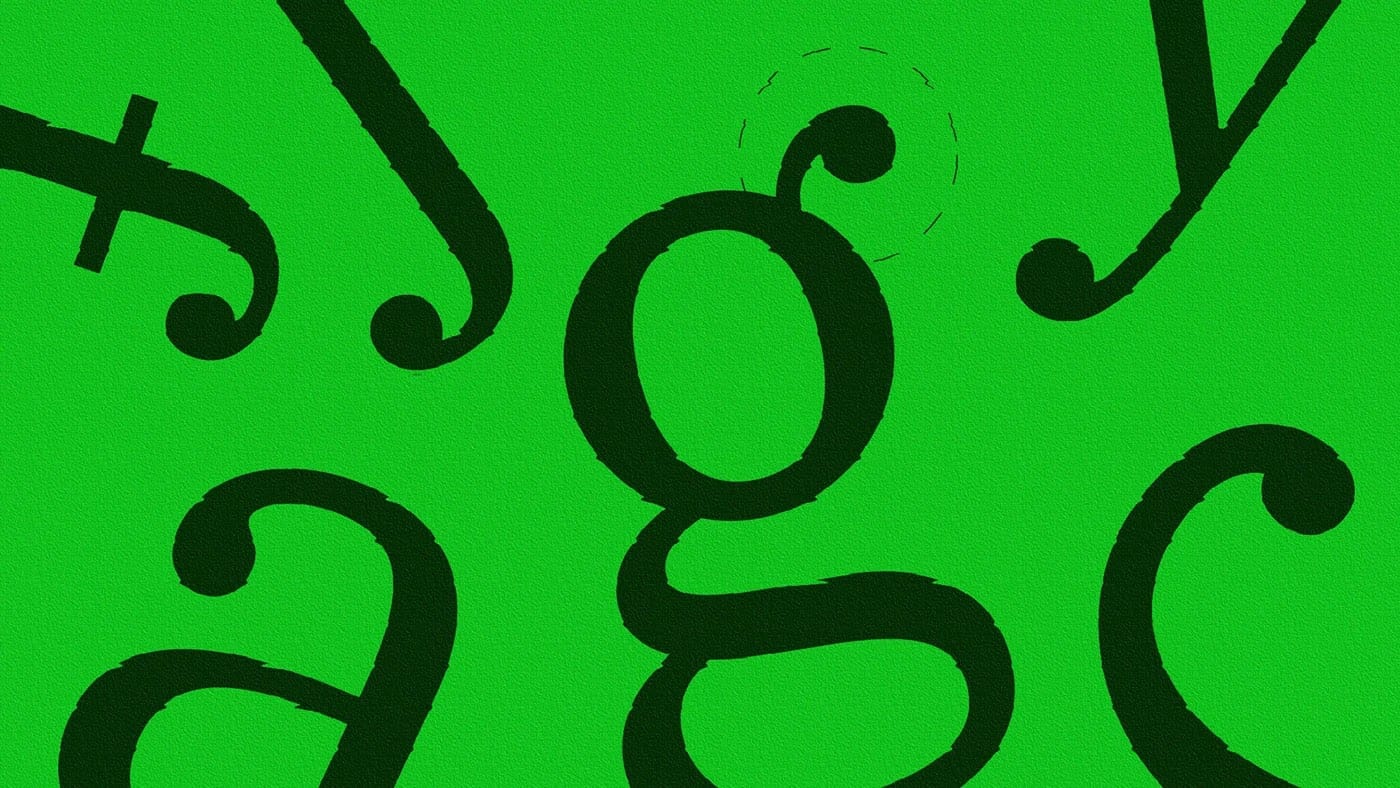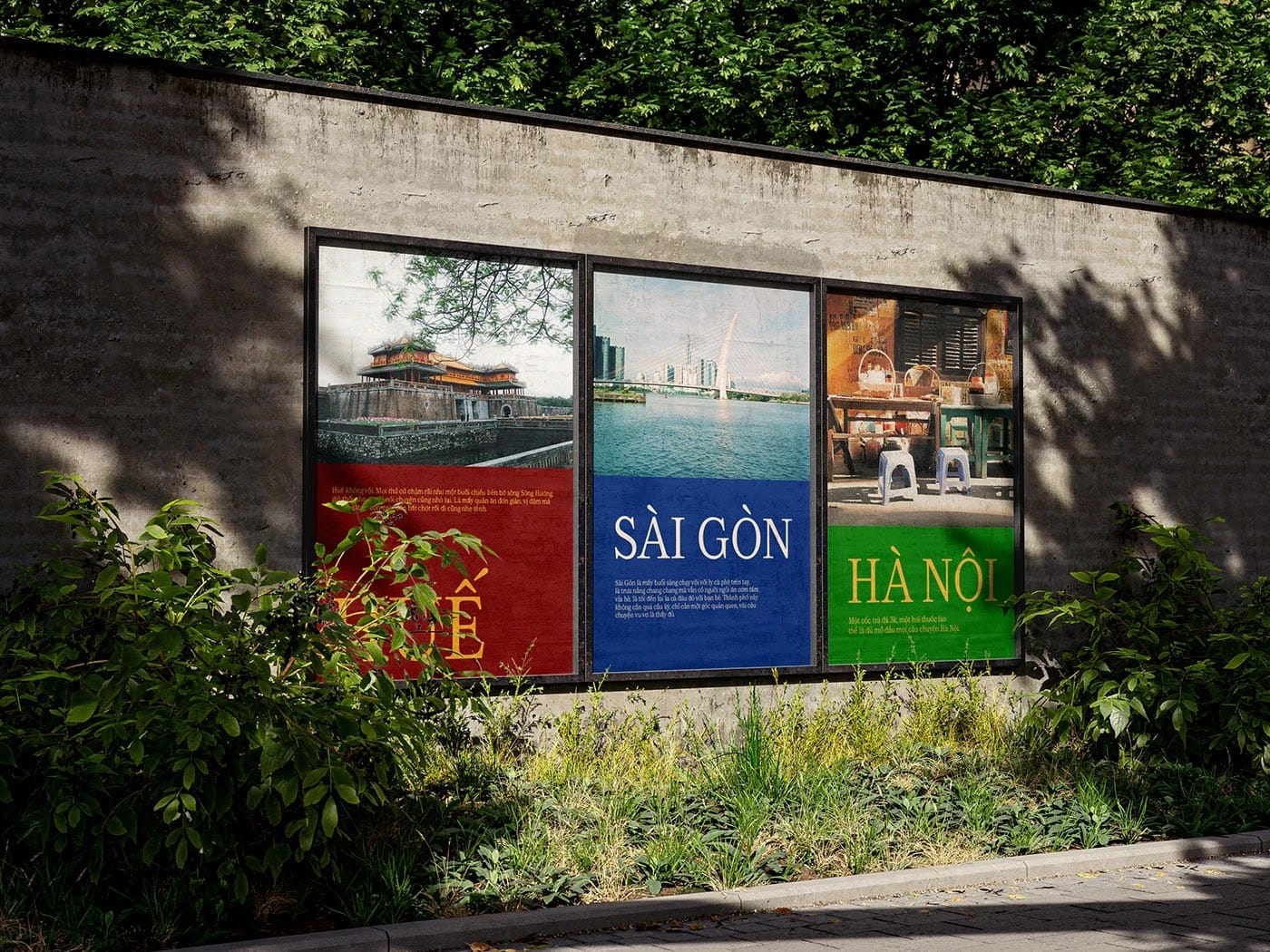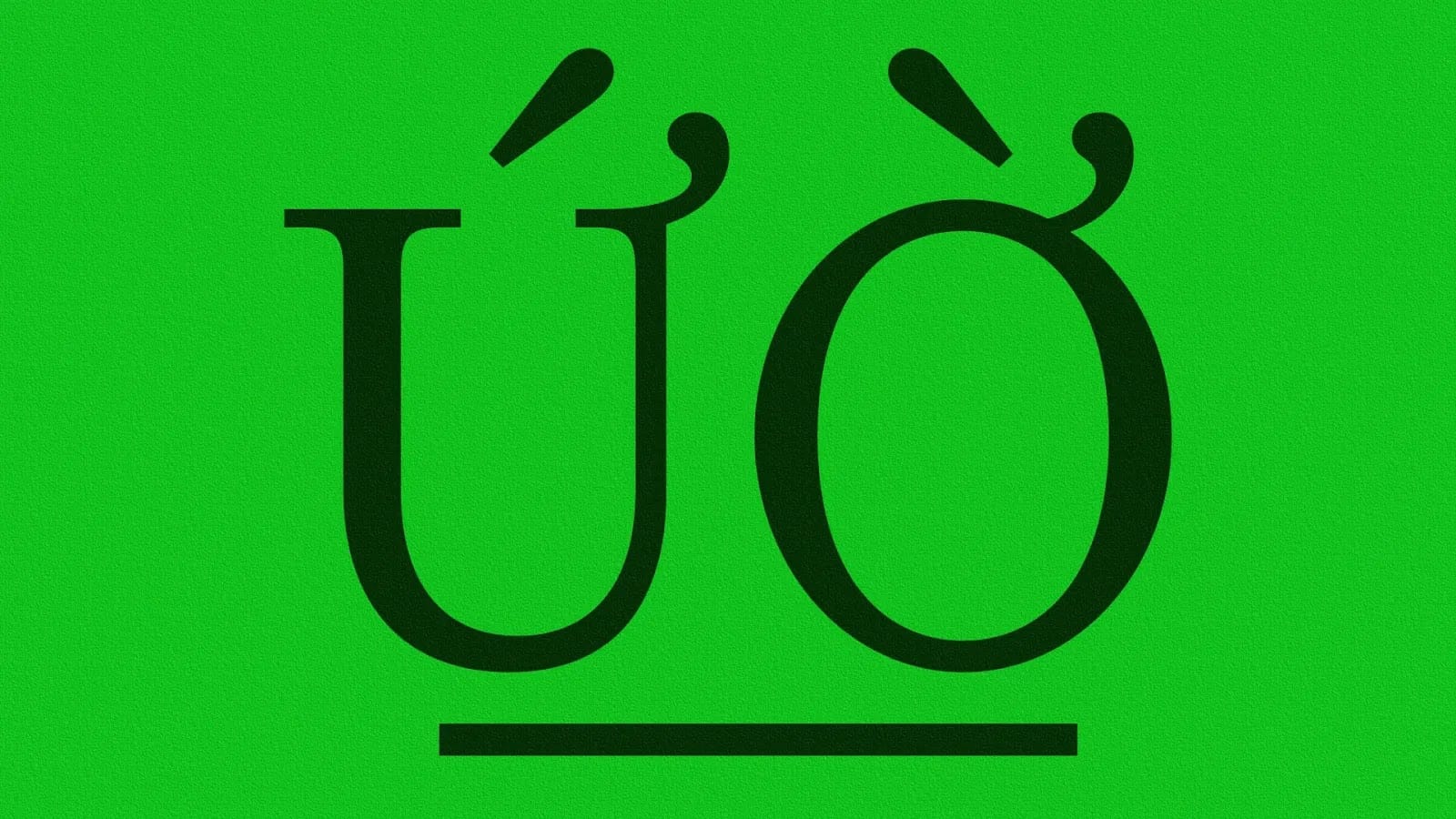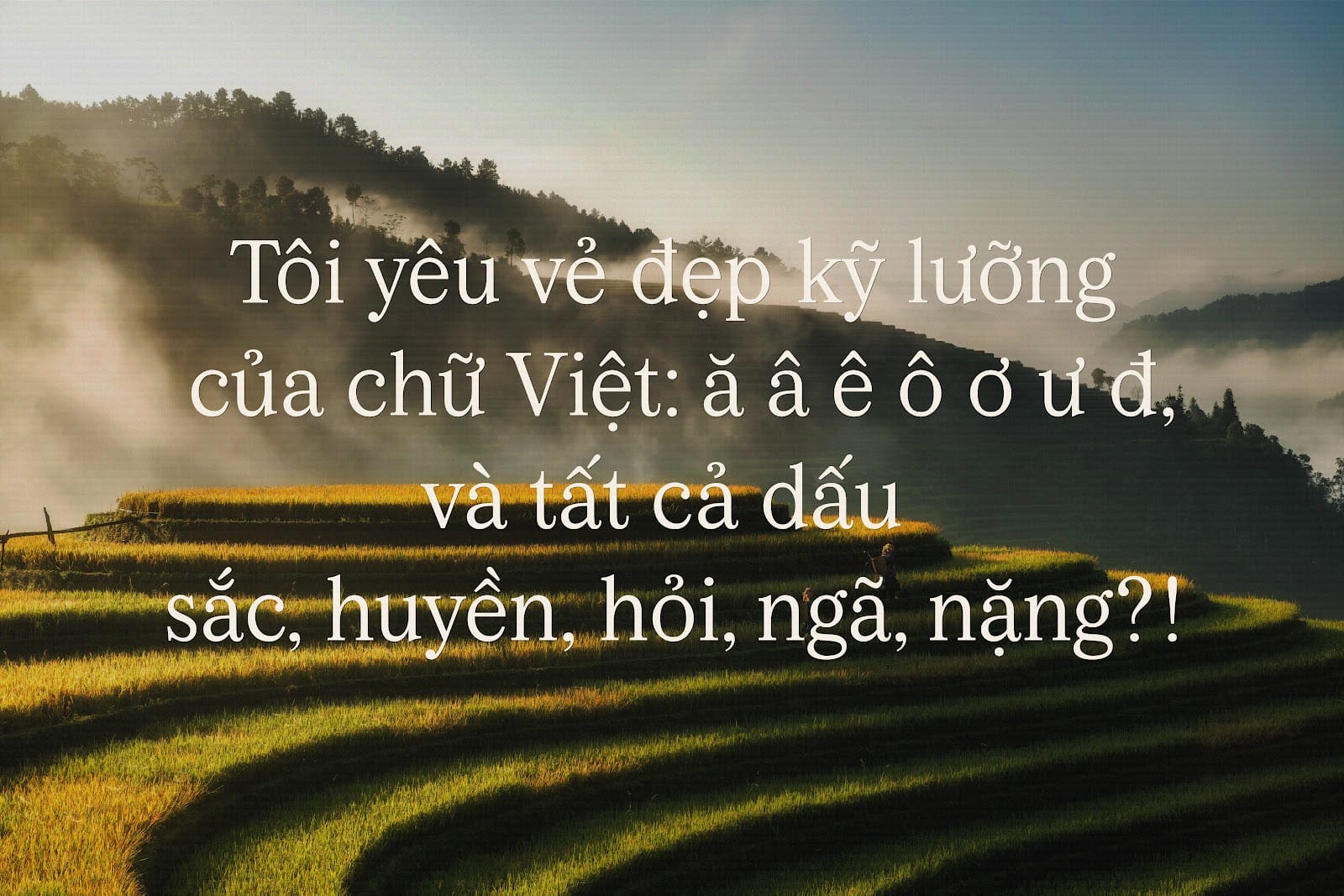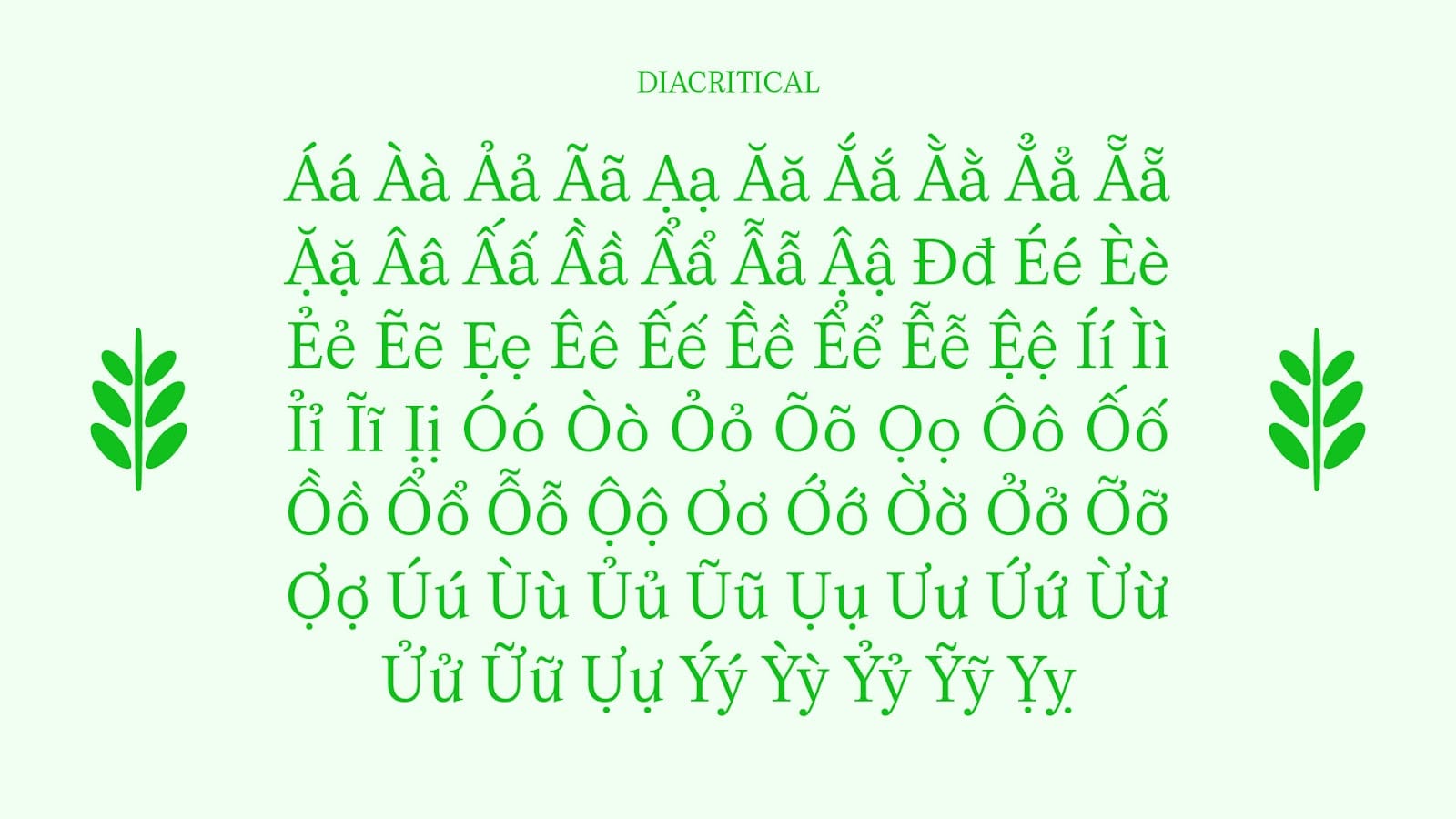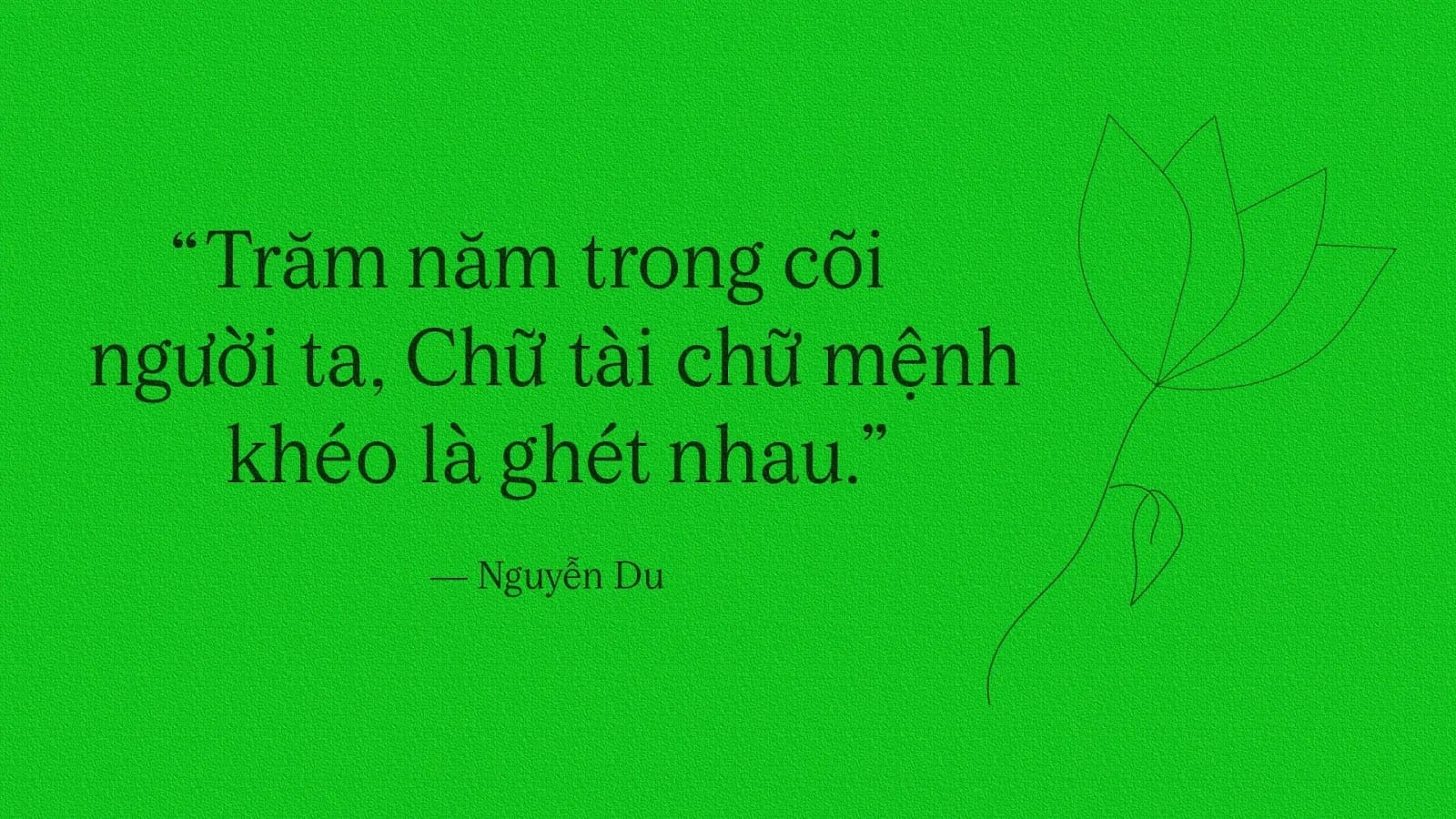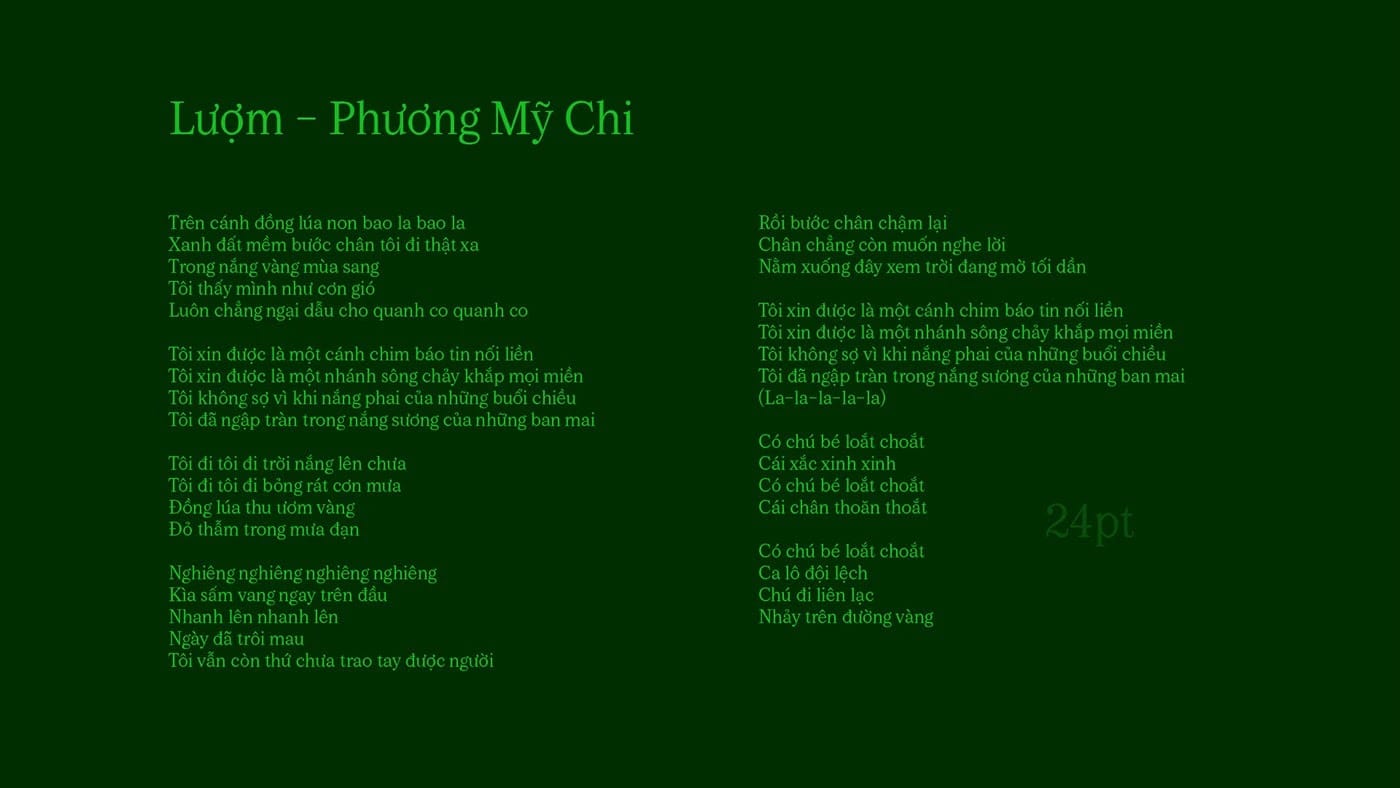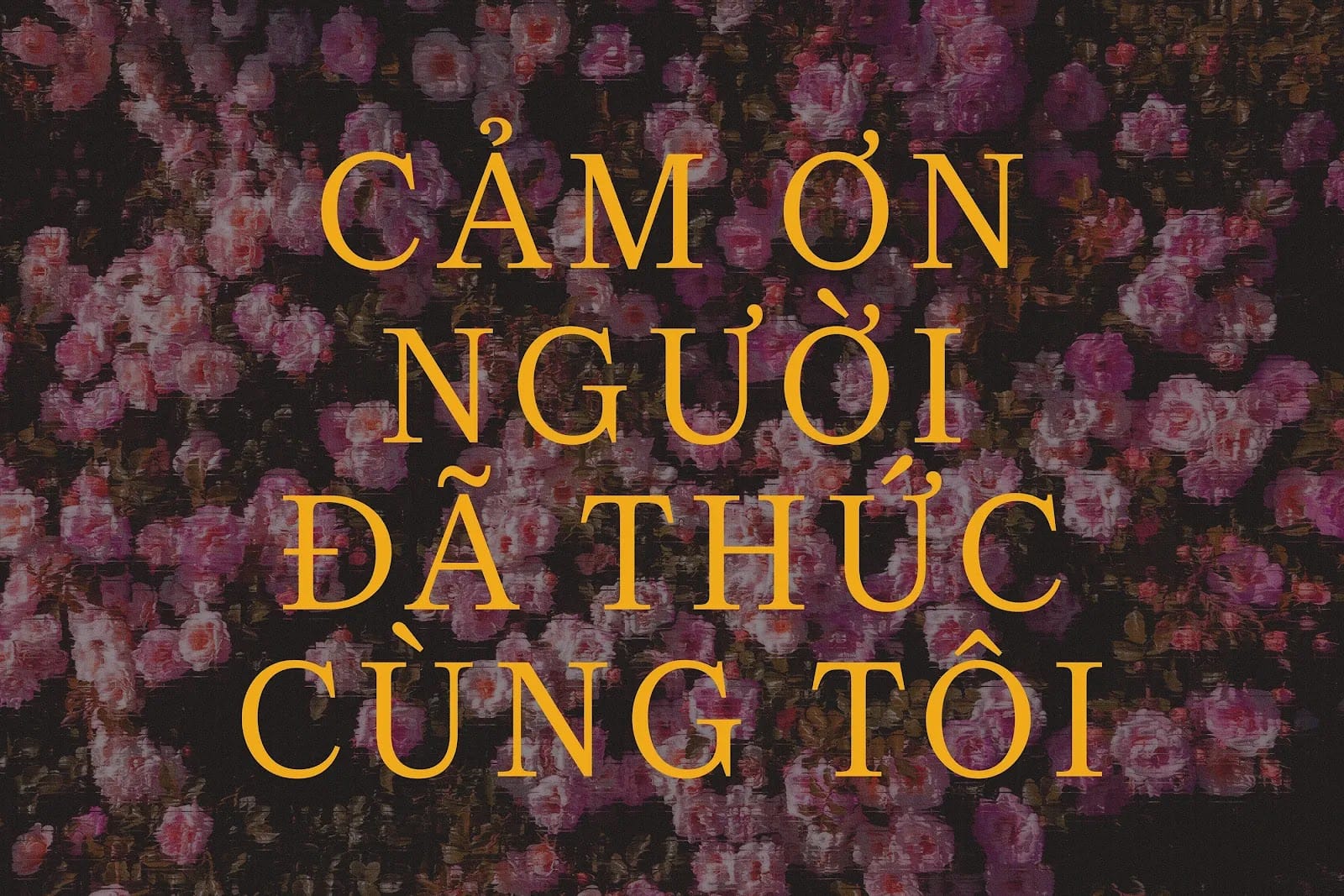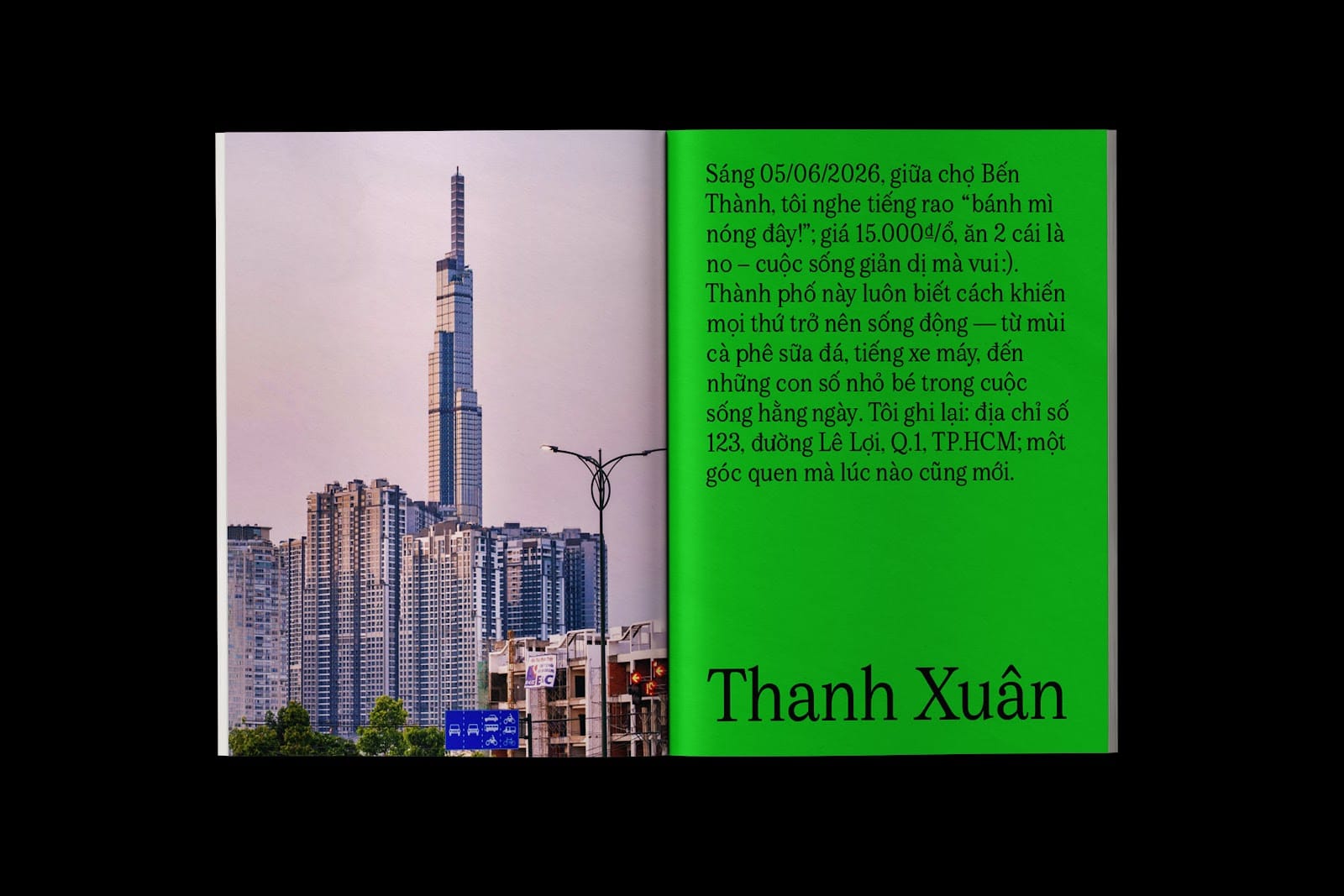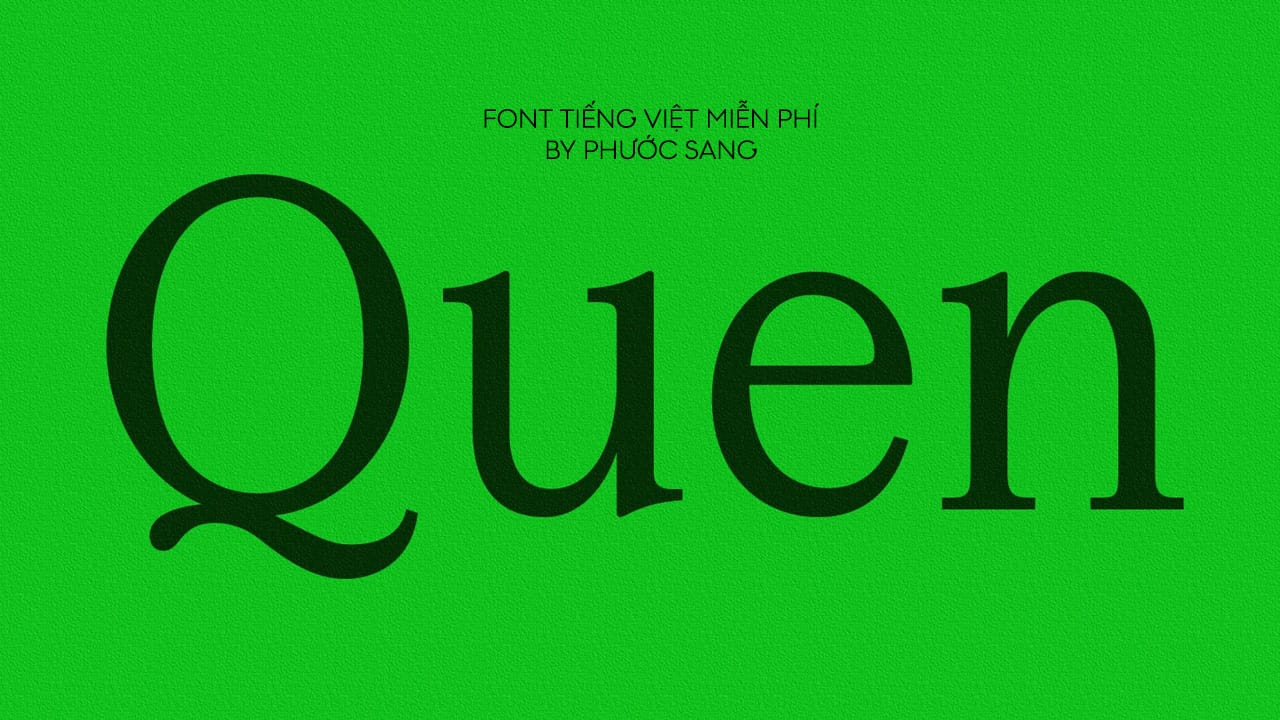
Quen là font serif mang tinh thần cổ điển pha hiện đại, lấy cảm hứng từ dòng transitional như Baskerville. Trục đứng vững vàng kết hợp cùng các ball terminal tròn tạo cảm giác ấm áp và tinh tế. Những đường cong ở Q và R mang lại cá tính riêng, góp phần tạo nên nhịp điệu thị giác mềm mại.
X-height cao giúp cải thiện khả năng đọc ở kích thước nhỏ, đồng thời được tối ưu cho hệ dấu tiếng Việt. Tổng thể, Quen cân bằng giữa truyền thống và biểu cảm, phù hợp cho tiêu đề và các ấn phẩm editorial.